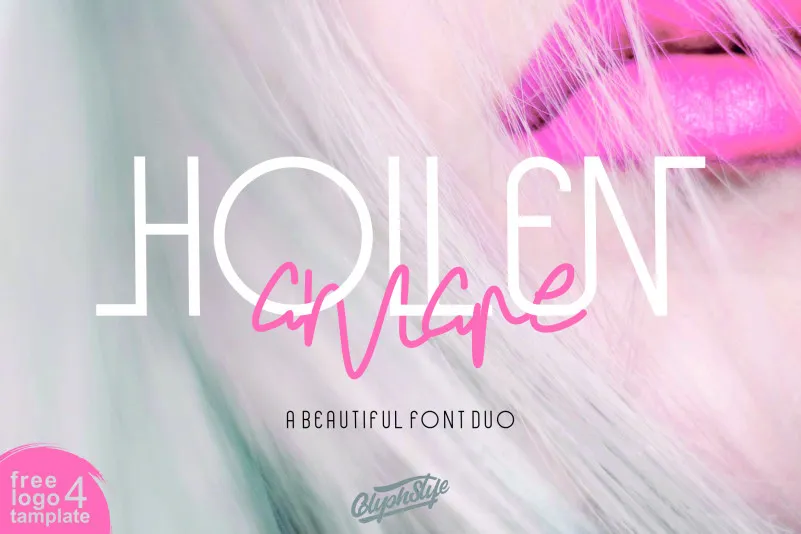
Hollen Amare Font Duo – Download Grátis
Hollen Amare Font Duo é uma dupla elegante composta por Hollen Amare Regular e Hollen Amare Script. Este duo de fontes foi criado para atender a uma ampla variedade de projetos gráficos, especialmente aqueles que buscam um toque autêntico e sofisticado. Perfectamente adequados para logotipos luxuosos, anúncios, cartões de visita, embalagens, postais, marcas, fotografia e até mesmo o registro de água, Hollen Amare é uma escolha perfeita para aqueles projetos que desejam incorporar uma sensação de escrita à mão com escrever vertical. Com sua elegância e sofisticação, essa dupla de fontes é uma excelente opção para quem busca trazer um toque único a qualquer projeto.